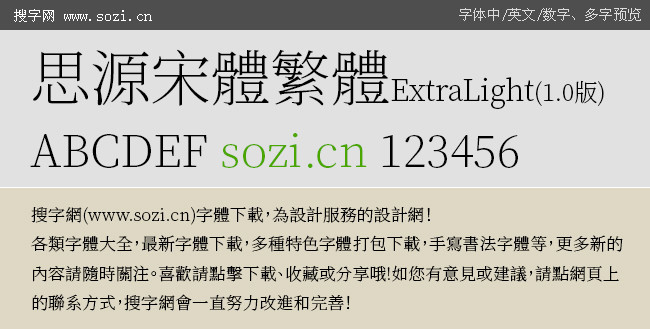
思源宋體繁體ExtraLight
搜字網(wǎng)提供一思源宋體繁體ExtraLight中文字體下載,思源宋體是一款由谷歌聯(lián)合Adobe發(fā)布全新開源字體,是一款免費、開源宋體字體。有 65535 個字形,可共同呈現(xiàn)一致的視覺美感。ExtraLight是一款比較細的字重,本作品適用于書籍排版、報紙排版、畫冊設(shè)計,網(wǎng)頁設(shè)計等應(yīng)用。